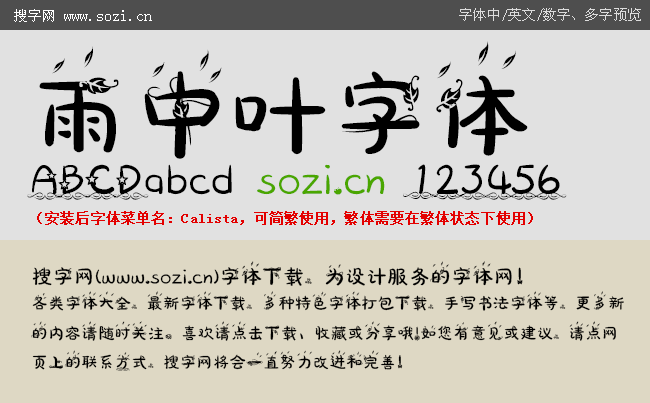
雨中葉字體
搜字網(wǎng)給大家提供一款很卡通的手機(jī)中文字體下載。修改者給這款字體叫雨中葉字體,這款手機(jī)中文字體以POP字體為原形,在筆畫間嵌入雨滴與花葉等卡通圖形,該中文字體趣味性強(qiáng),又保持了文字的識(shí)別度,非常適合喜歡卡通的朋友在手機(jī)上安裝使用。